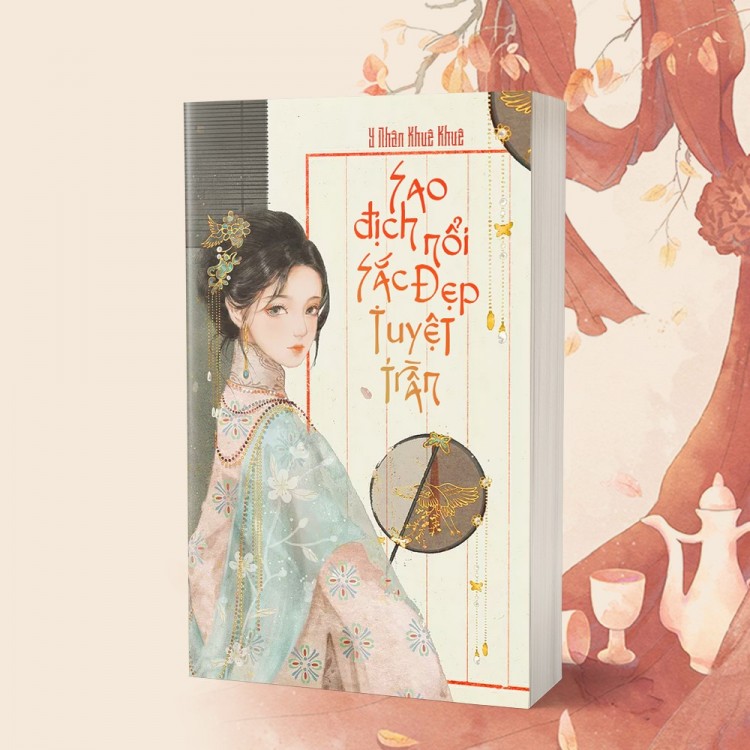
Giới thiệu về Font việt hóa Snotmaster V
Trong thế giới thiết kế đồ họa hiện đại, việc lựa chọn một Font Chữ phù hợp đóng vai trò then chốt giúp truyền tải thông điệp hiệu quả. Font việt hóa Snotmaster V nổi lên như một sự lựa chọn hàng đầu nhờ phong cách độc đáo và cá tính mạnh mẽ. Đây là bộ phông chữ được tinh chỉnh kỹ lưỡng để hỗ trợ đầy đủ bảng mã tiếng Việt, giúp người dùng không còn lo lắng về lỗi hiển thị dấu khi thiết kế các ấn phẩm truyền thông hay học tập.
Đặc điểm nổi bật của Snotmaster V
Thiết kế hiện đại và linh hoạt
Bộ font này sở hữu những đường nét thanh thoát nhưng không kém phần phá cách, tạo nên sự cân bằng hoàn hảo giữa tính nghệ thuật và ứng dụng thực tế. Snotmaster V cực kỳ phù hợp cho các dự án thiết kế tiêu đề sách, bìa báo tường, hoặc các bài thuyết trình tại trường học. Khả năng hiển thị rõ nét trên cả màn hình kỹ thuật số và bản in giúp sản phẩm của bạn luôn chuyên nghiệp trong mắt người xem.
Hỗ trợ tiếng Việt hoàn chỉnh
Điểm mạnh nhất của phiên bản này chính là việc tối ưu hóa các ký tự đặc biệt của tiếng Việt. Các dấu thanh như huyền, sắc, hỏi, ngã, nặng được đặt ở vị trí hợp lý, đảm bảo tính thẩm mỹ cao nhất. Người dùng có thể dễ dàng cài đặt và sử dụng trên nhiều phần mềm khác nhau như Photoshop, Canva hay Microsoft Word mà không gặp bất kỳ trở ngại nào về kỹ thuật.
Lợi ích khi sử dụng Font việt hóa Snotmaster V